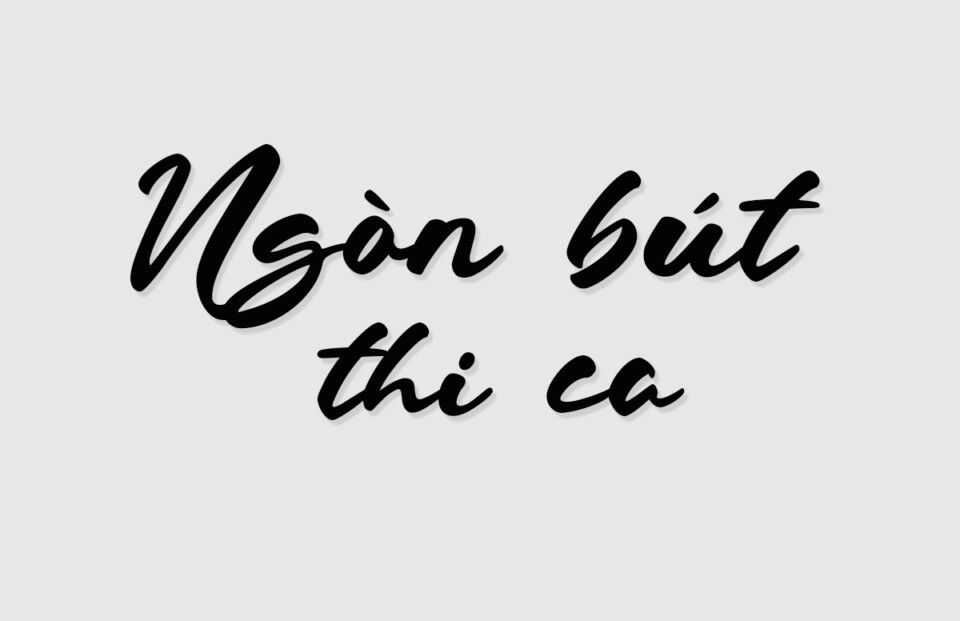
Font Việt hóa 1FTV VIP Baleday là bộ phông chữ nghệ thuật cao cấp được tinh chỉnh tỉ mỉ, mang phong cách hiện đại và đầy sức hút dành riêng cho cộng đồng thiết kế đồ họa. Với việc tích hợp trọn vẹn bộ dấu tiếng Việt chuẩn xác, sản phẩm giúp các nhà thiết kế dễ dàng hiện thực hóa mọi ý tưởng sáng tạo từ logo, bao bì đến các chiến dịch truyền thông đỉnh cao. Hãy cùng khám phá chi tiết những ưu điểm vượt trội và khả năng ứng dụng đa dạng của bộ phông chữ đẳng cấp này ngay trong bài viết dưới đây.
Font Việt Hóa 1FTV VIP Baleday – Giải Pháp Typography Đỉnh Cao Cho Thiết Kế Đồ Họa Modern
Trong thế giới thiết kế đồ họa đầy tính cạnh tranh hiện nay, typography đóng vai trò then chốt trong việc định hình cảm xúc và truyền tải thông điệp của thương hiệu. Một bộ font chữ đẹp không chỉ thu hút thị giác người xem ngay từ ánh nhìn đầu tiên mà còn thể hiện được cái thần, chiều sâu và sự chuyên nghiệp của toàn bộ tác phẩm. Tuy nhiên, rào cản lớn nhất đối với các designer tại Việt Nam chính là việc nhiều font chữ quốc tế ấn tượng thường bị lỗi hiển thị, vỡ nét hoặc dính dấu khi gõ tiếng Việt có dấu. Sự ra đời của Font Việt hóa 1FTV VIP Baleday đã giải quyết triệt để vấn đề này, mang đến một giải pháp sáng tạo toàn diện, mượt mà và đạt chuẩn thẩm mỹ cao nhất.
Bộ font 1FTV VIP Baleday được chăm chút tỉ mỉ từng đường nét, góc uốn cho đến vị trí đặt dấu thanh sao cho cân đối và tự nhiên nhất. Sự kết hợp hoàn hảo giữa đường nét sang trọng cổ điển và hơi thở hiện đại giúp font chữ này dễ dàng chinh phục mọi góc nhìn. Cho dù bạn đang thực hiện các dự án thiết kế nhận diện thương hiệu cao cấp, poster sự kiện, bìa tạp chí, bao bì sản phẩm hay các ấn phẩm truyền thông mạng xã hội, 1FTV VIP Baleday đều có thể giúp tác phẩm của bạn tỏa sáng một cách vô cùng ấn tượng.
1. Việt Hóa Chuẩn Xác 100% Và Tối Ưu Hóa Ký Tự Tiếng Việt <p>Điểm cộng lớn nhất của 1FTV VIP Baleday chính là quá trình Việt hóa được thực hiện vô cùng công phu và chuẩn xác. Hệ thống dấu thanh như sắc, huyền, hỏi, ngã, nặng cùng các ký tự đặc thù của tiếng Việt (ă, ê, ô, ơ, ư, đ) được thiết kế đồng bộ hoàn hảo với cấu trúc chữ gốc. Khoảng cách giữa các ký tự (kerning) và độ cao dòng (leading) được căn chỉnh tự động, giúp văn bản gõ ra không bị lệch dấu, dính chữ hay phá vỡ bố cục tổng thể của bản vẽ.
Dấu Thanh Tinh Tế: Dấu thanh được vẽ lại tỉ mỉ, giữ nguyên tỉ lệ vàng của nét chữ gốc, đảm bảo tính thẩm mỹ cao nhất ngay cả khi thu nhỏ làm chi tiết phụ hoặc phóng to làm tiêu đề.
Không Lỗi Hiển Thị: Loại bỏ hoàn toàn tình trạng mất dấu, lỗi ô vuông hoặc biến dạng ký tự khi xuất file in ấn hoặc làm thiết kế kỹ thuật số.
2. Phong Cách Thiết Kế Sang Trọng, Đa Dạng Và Tạo Điểm Nhấn Ấn Tượng
Font Việt hóa 1FTV VIP Baleday sở hữu ngôn ngữ thiết kế độc đáo với những đường nét vừa cá tính vừa mượt mà. Tỷ lệ giữa các nét thanh và nét đậm được tính toán kỹ lưỡng, tạo nên độ tương phản thị giác vừa đủ để thu hút ánh nhìn nhưng không gây cảm giác rối mắt. Đây là sự lựa chọn lý tưởng cho các tựa đề chính (headline), logo thương hiệu hay các đoạn văn bản ngắn cần tạo sự chú ý mạnh mẽ.
Đường Nét Độc Đáo: Sự pha trộn hoàn hảo giữa nét uốn lượn nghệ thuật và cấu trúc hình học hiện đại.
Tính Sang Trọng High-End: Thích hợp cho các ngành hàng thời trang, mỹ phẩm, trang sức, bất động sản cao cấp và sự kiện sang trọng.
Độ Linh Hoạt Cao: Dễ dàng phối hợp với các font chữ phụ dạng Sans-serif hoặc Serif tối giản để tạo nên bộ đôi typography cân bằng.
3. Tích Hợp Ký Tự Thay Thế (Alternates) Và Nét Uốn Nghệ Thuật (Swashes)
Nhằm đáp ứng nhu cầu sáng tạo không giới hạn của giới thiết kế, 1FTV VIP Baleday được trang bị hệ thống tính năng OpenType vô cùng phong phú. Bộ font cung cấp hàng loạt ký tự thay thế (Stylistic Alternates), ký tự ghép bộ (Ligatures) và các nét đuôi uốn lượn nghệ thuật (Swashes). Bạn có thể tùy biến các chữ cái đầu hoặc chữ cái cuối câu để tạo nên những tác phẩm chữ độc bản như được vẽ tay thủ công.
Stylistic Sets Đa Dạng: Cho phép biến đổi kiểu dáng của từng chữ cái chỉ bằng vài cú click chuột trong các phần mềm thiết kế chuyên nghiệp.
Ligatures Thông Minh: Tự động kết nối các cặp chữ cái đi liền nhau một cách mượt mà và tự nhiên nhất.
Tự Do Sáng Tạo Logo: Giúp các designer dễ dàng tạo ra biểu trưng thương hiệu (logotype) ấn tượng mà không cần tốn quá nhiều thời gian dựng hình từ đầu.
4. Khả Năng Ứng Dụng Linh Hoạt Trên Nhiều Nền Tảng Và Sản Phẩm Thiết Kế
Không bị giới hạn trong một lĩnh vực cụ thể, Font Việt hóa 1FTV VIP Baleday tỏ ra vô cùng đa năng khi có thể ứng dụng xuất sắc trên nhiều chất liệu và nền tảng khác nhau. Từ các ấn phẩm in ấn truyền thống đến các sản phẩm truyền thông kỹ thuật số (digital marketing), bộ font này đều giữ vững phong độ và khả năng hiển thị vượt trội.